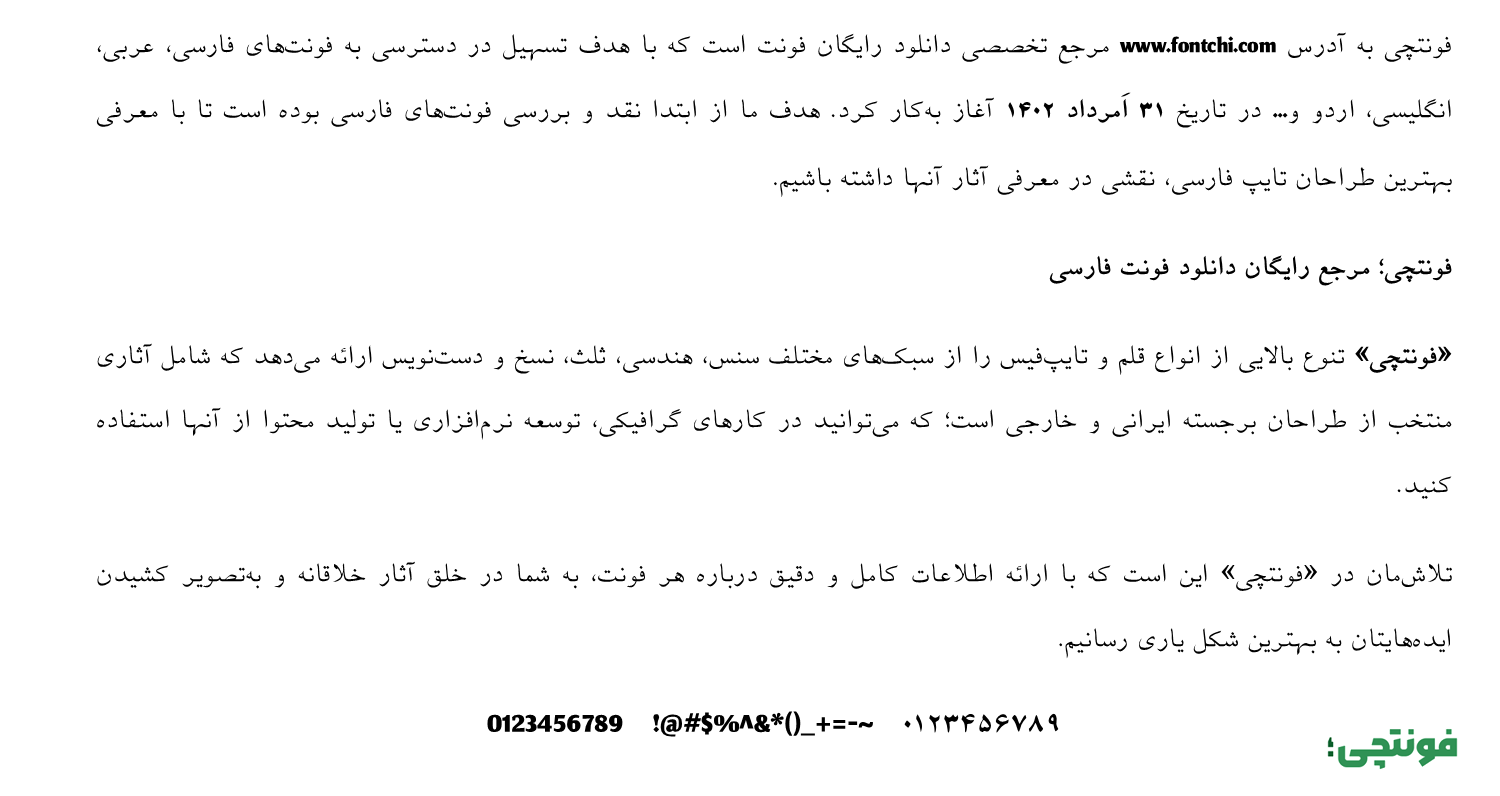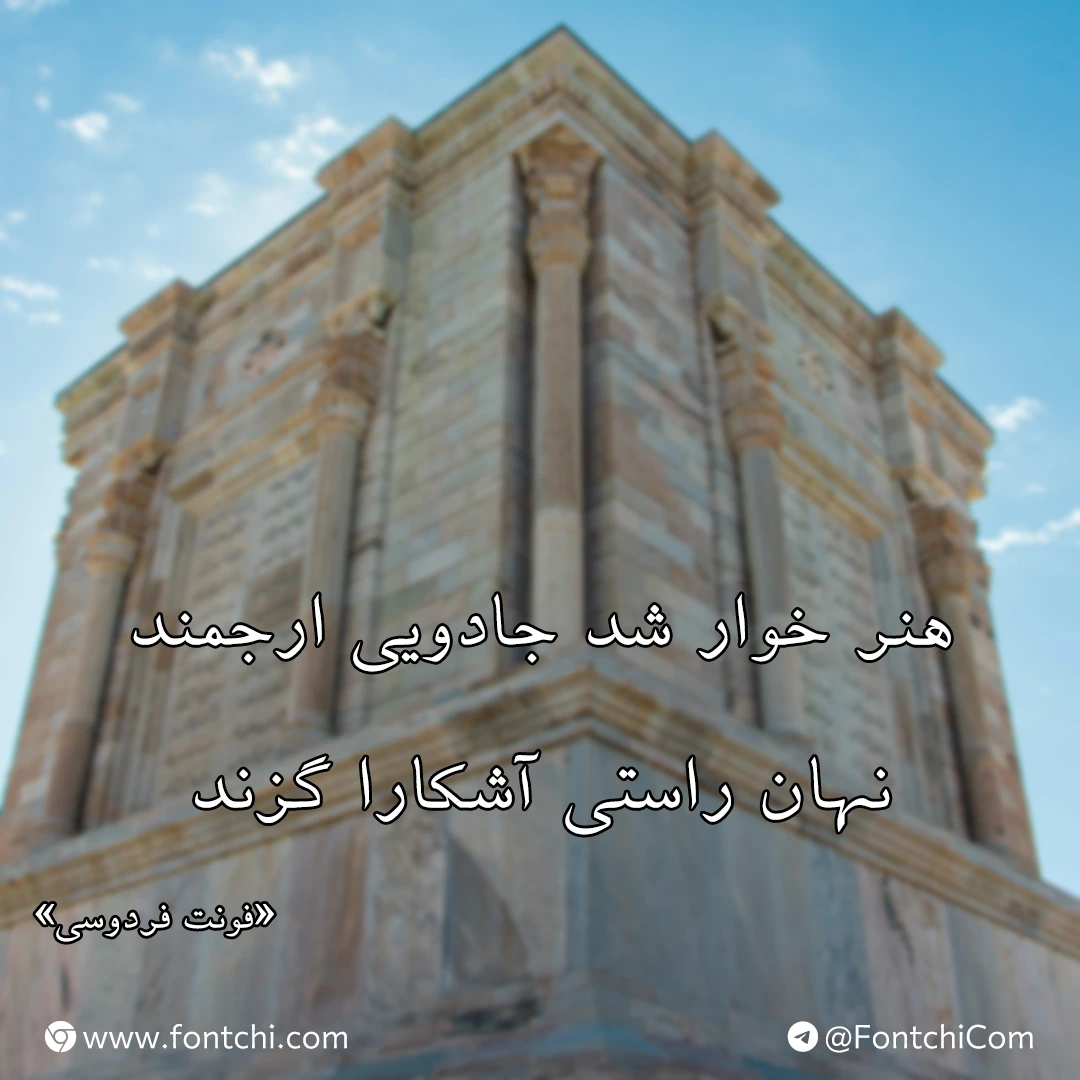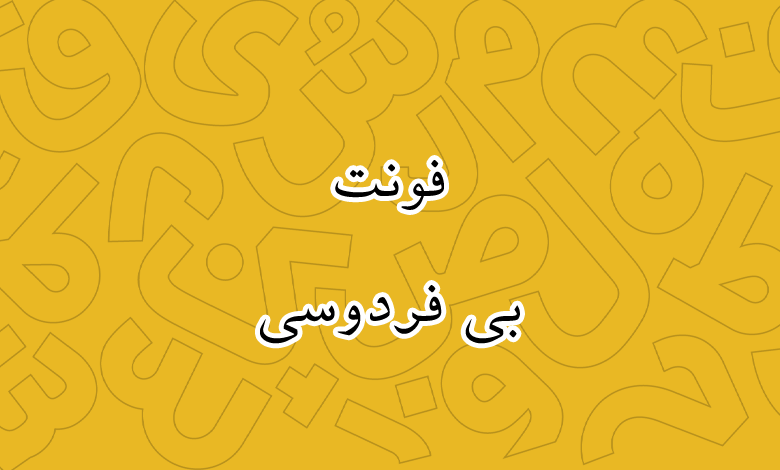
فونت فردوسی (B Ferdosi)
فونت فردوسی یا بی فردوسی (به انگلیسی: B Ferdosi) از دیگر فونتهای طراحی شده توسط شرکت برنا رایانه در دهه هفتاد است که میتوانید از آن برای متون بلند استفاده کنید. این فونت بیشتر برای مطبوعات، متن کتاب و حوزه چاپ کاربرد دارد.
سبک طراحی فونت فردوسی کلاسیک و برگرفته از خط نستعلیق است، اما با ساختاری سادهتر و مدرنتر که میتوان از آن در متون بلند و حتی رسمی استفاده کرد. در این فونت تلاش شده تعادلی بین زیبایی خطوط سنتی و کاربردپذیری در محیطهای دیجیتال برقرار شود.
فونت بی فردوسی از زبان فارسی و عربی پشتیبانی نسبتا کاملی دارد. تمامی گلیفهای مشترک بین این دو زبان با ظاهر استاندارد خود طراحی شدهاند و تنها در بخش اعداد است که شاهد استفاده از اعداد تماما فارسی بهجای اعداد عربی «۰۴۵۶» هستیم. برای زبان انگلیسی طراحی اختصاصی نداشته و از فونت پیشفرض استفاده شده است.
فونت فردوسی از تمامی اعراب زبان فارسی و عربی به شکل استانداردی پشتیبانی میکند و برای متون اردو نیز تا حد زیادی میتوانید از آن استفاده کنید.
این فونت فارسی برای طراحی پوستر، کتاب، مجلات، لوگوتایپ و حتی رابط کاربری دیجیتال مناسب است. بهویژه در پروژههایی که نیاز به حس و حال فرهنگی و سنتی ایرانی دارند، بسیار مورد توجه قرار میگیرد.
برخلاف برخی فونتهای سنتی که در اندازههای کوچک دچار مشکل میشوند، فونت B Ferdosi در متون کوچک و بزرگ عملکرد خوبی داشته و وانایی بسیار خوبی از خود نشان میدهد. طراحی این فونت با الهام از خطوط سنتی ایرانی، حس اصالت و هویت فرهنگی را منتقل میکند. خطوط نرم و انحناهای ظریف آن بهویژه در عناوین و تیترها جلوهای چشمنواز ایجاد میکند.
تنوع وزن فونت فردوسی محدود بوده و صرفا از یک وزن معمولی (Regular) پشتیبانی میکند. این وزن فونت دارای ظاهری معمولی است که برای استفاده در متون بلند مناسب است. در حالی که اگر برای عناوین بخواهید استفاده کنید، آن ظاهر بولدی که انتظار داشته باشید را برآورده نخواهد کرد.
با اینکه کاربرد عمده این فونت در متون بلند است، اما استفاده برای متون بسیار طولانی مثل کتابهای چندصد صفحهای ممکن است به دلیل سبک سنتیاش کمی خستهکننده باشد و خوانایی آن در مقایسه با فونتهای مدرنتری مانند B Nazanin یا B Mitra کاهش یابد.
حس سنتی این فونت برای انتقال فرهنگ ایرانی مناسب است که به همین دلیل نیز با نام حکیم فردوسی نامگذاری شده است. اگر به دنبال فونتی مدرنتر در سبک نستعلیق هستید، میتوانید از این قلم استفاده کنید.